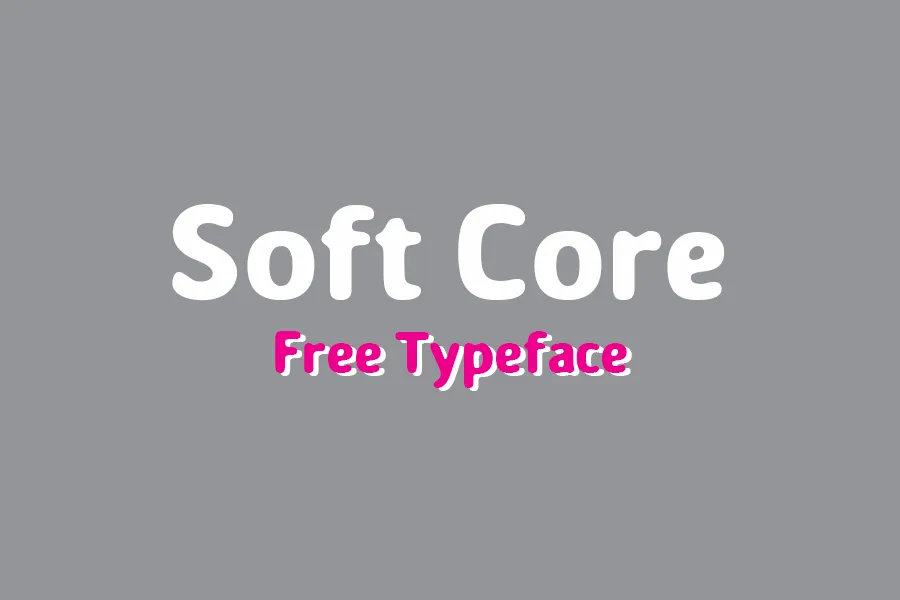
Introduzimos a Soft Core Font! Desenhada e compartilhada pela Ungrund Studio, a font ‘Soft Core’ é uma versão redonda do famoso ‘Core’ font. Esta tipografia perfeita para crianças ganha vida como um personagem de quadrinhos, em livros infantis, produtos feitos especialmente para eles ou até mesmo em logotipos. É inegável que a Soft Core Font tem seu próprio espaço e habitat natural, fazendo das suas aparições cada vez mais divertidas e criativas. Ainda assim, é uma font perfeita para qualquer desafio de design. Essa elegância e suavidade em cada letra é ideal para criar um ambiente confortável e alegre que cativa não apenas as crianças, mas também os adultos. Quer seja para cartazes infantis, materiais educativos ou até mesmo para gráficos publicitários focados no público jovem, a Soft Core Font está pronta para se integrar perfeitamente em qualquer projeto. Tornando-se sua escolha ideal quando você busca uma fonte com um visual suave e reconfortante. Não espere mais para adicionar a graça da vida aos seus projetos!